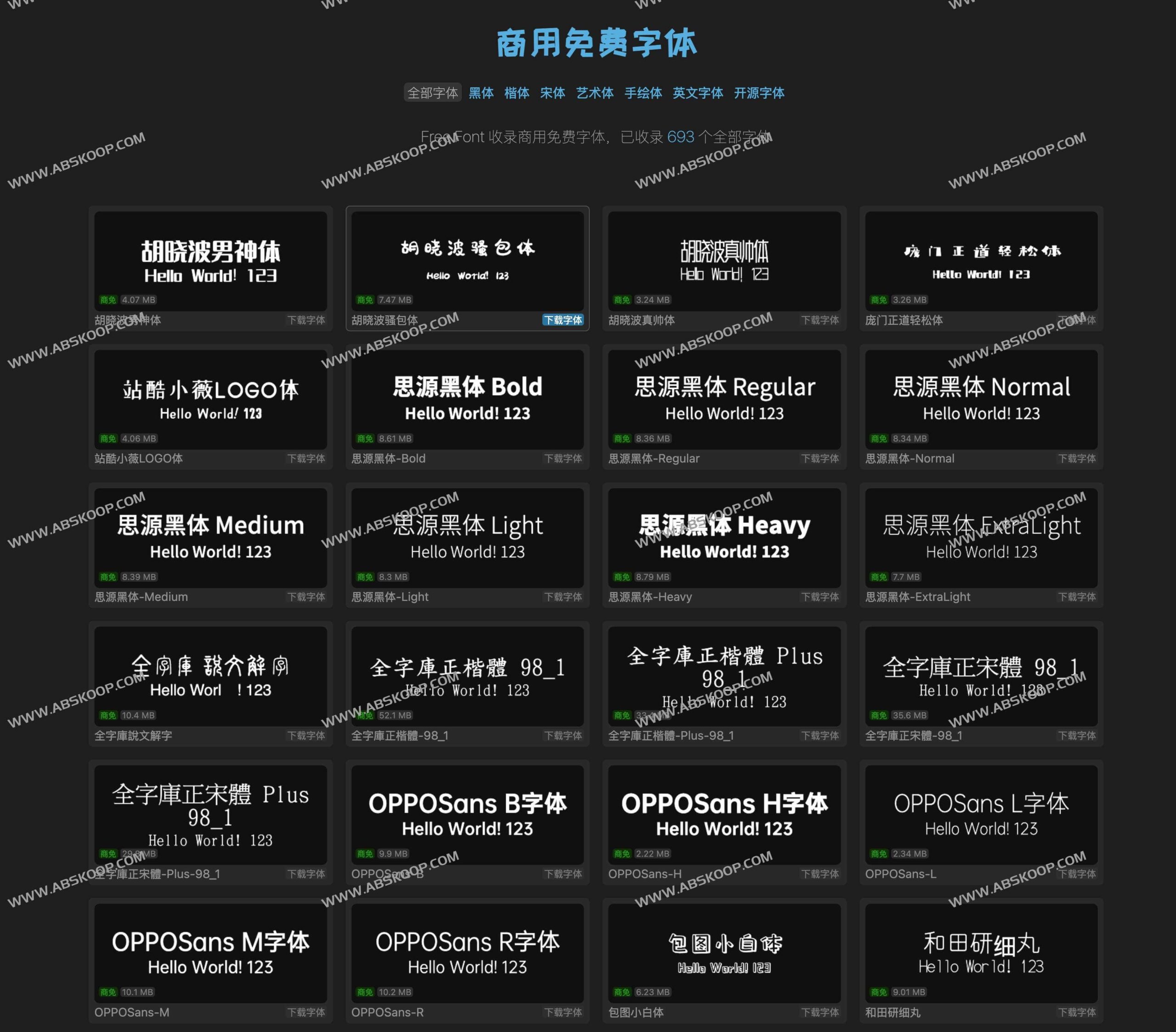
商用免版权中英文字体库:涵盖开源免费资源及其授权细节指南
Free Font:一站式商用免费字体资源库
Free Font 是一个专门收录可商用免费字体的在线资源平台,旨在为设计者和内容创作者提供一个无需担心版权风险的字体获取渠道。
资源覆盖与项目背景
该项目在原有的字集开源项目基础上进行了深度扩展,重新梳理并增补了大量优质的中文字体及开源英文字体,目前已累计收录 693 种字体。其资源分类广泛,涵盖了多种视觉风格:
• 经典实用: 黑体、宋体、楷体
• 创意视觉: 艺术体、手绘体
• 国际化需求: 各类开源英文字体
适用场景